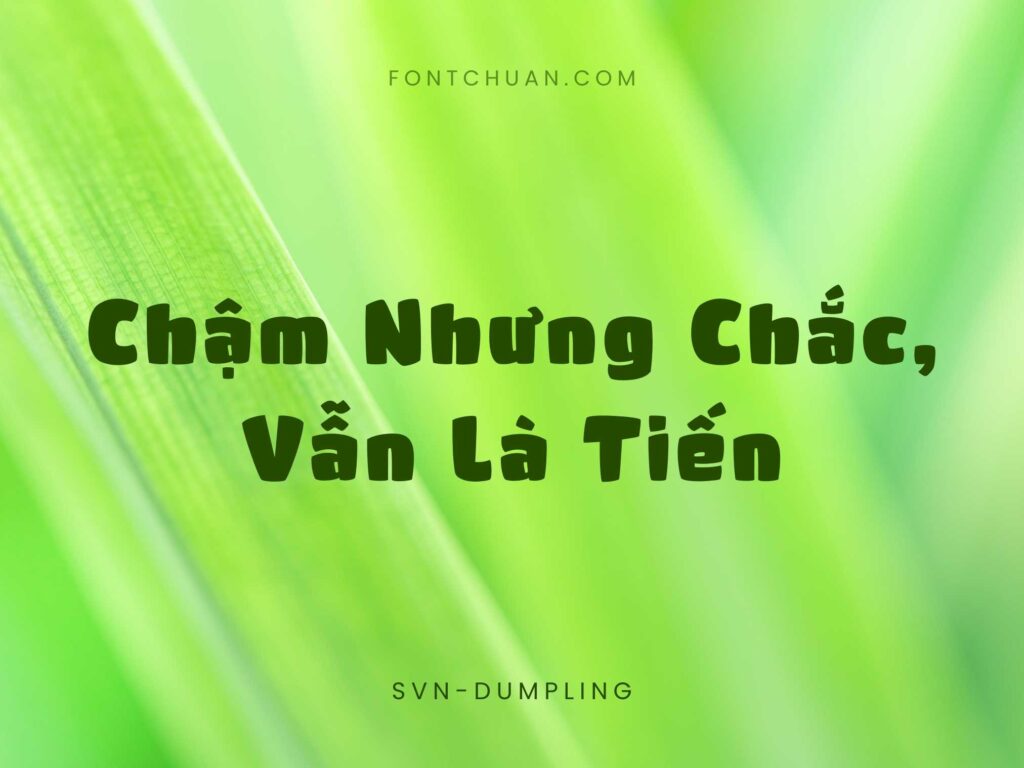
Font SVN Dumpling Việt Hóa
Tác giả Font: Mary Catherine Pflug, Neil Summerour
Dumpling là một font chữ hoạt hình vui nhộn, được thiết kế bởi TMT. Font này mang lại cảm giác trẻ trung và dễ thương, phù hợp cho các dự án thiết kế liên quan đến trẻ em, đồ ăn hoặc các sản phẩm vui nhộn. Font đã được Việt hóa để hỗ trợ tiếng Việt bởi S99.VN, đồng thời hỗ trợ nhiều ngôn ngữ khác, giúp mở rộng phạm vi sử dụng trên toàn cầu. Font này được chia sẻ miễn phí cho mục đích sử dụng cá nhân; để sử dụng cho mục đích thương mại, bạn nên liên hệ với tác giả qua email: octotypeone@gmail.com.
Đặc điểm thiết kế của Dumpling bao gồm các nét chữ mềm mại và tròn trịa, tạo cảm giác thân thiện và gần gũi. Font này phù hợp cho các ứng dụng như tiêu đề, logo, thiệp mời, bao bì sản phẩm dành cho trẻ em và các dự án sáng tạo khác. Các ngành nghề phù hợp bao gồm quảng cáo, nghệ thuật và thiết kế đồ họa.